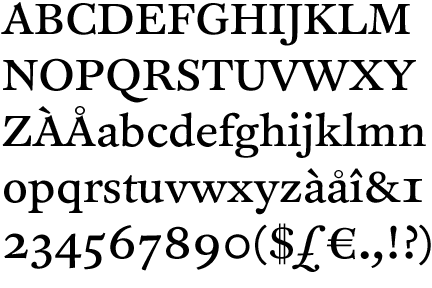
Clifford -> Barock?
Ich schreibe gerade eine Arbeit, bei der ich Schriften bestimmte Farben zuordne. Da ich mich ungern blamiere, hoffe ich auf Eure Hilfe: Schriftklassifikation ist leider nicht gerade meine Hausdisziplin. Da beschreibe ich die FF Clifford von Akira Kobayashi. In welche Klasse gehört die denn nun?
Die Schattenachse geht zur klassizistischen hin, die Schrift ist doch aber für eine barocke eher zu dynamisch, oder? Venezianische und klassizistische scheiden mit Sicherheit aus. Ist es nun eine französische Renaissance- oder eine barocke Antiqua?
Ich würde das als Renaissance-Antiqua klassifizieren.
Wobei z.B. der Abschwung des Versal-R atypisch ist.
Vergleiche selbst:
Wenn ich mir die Kleinbuchstaben ansehe, würde ich sagen typische Übergangsantiqua, also ja, Barock. Die Großbuchstaben haben ein paar Eigenheiten (z.B. A C M), aber das sind wohl die Feinheiten die diese konkrete Schrift dann ausmachen.
Diese Barock-Klasse ist ja so ein Ding... Die gibt es eigentlich gar nicht :)
Das war eher ein fließender Übergang, die Grenzbereiche zwischen Renaissance-, "Barock"- und klassizistischer Antiqua sind anhand konkreter Schriften kaum zu definieren. Je nach Land, Schriftschneider, etc. gibt es da Unterschiede.